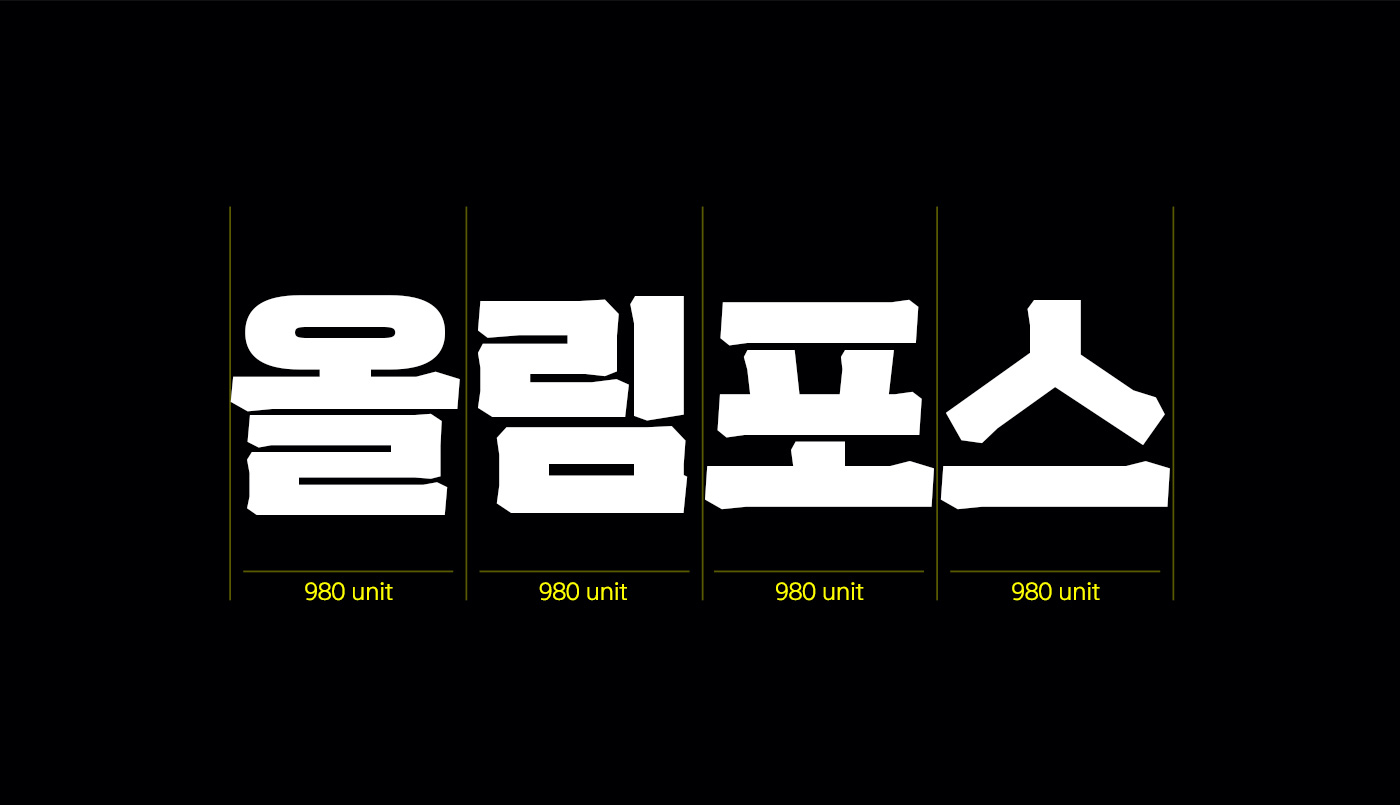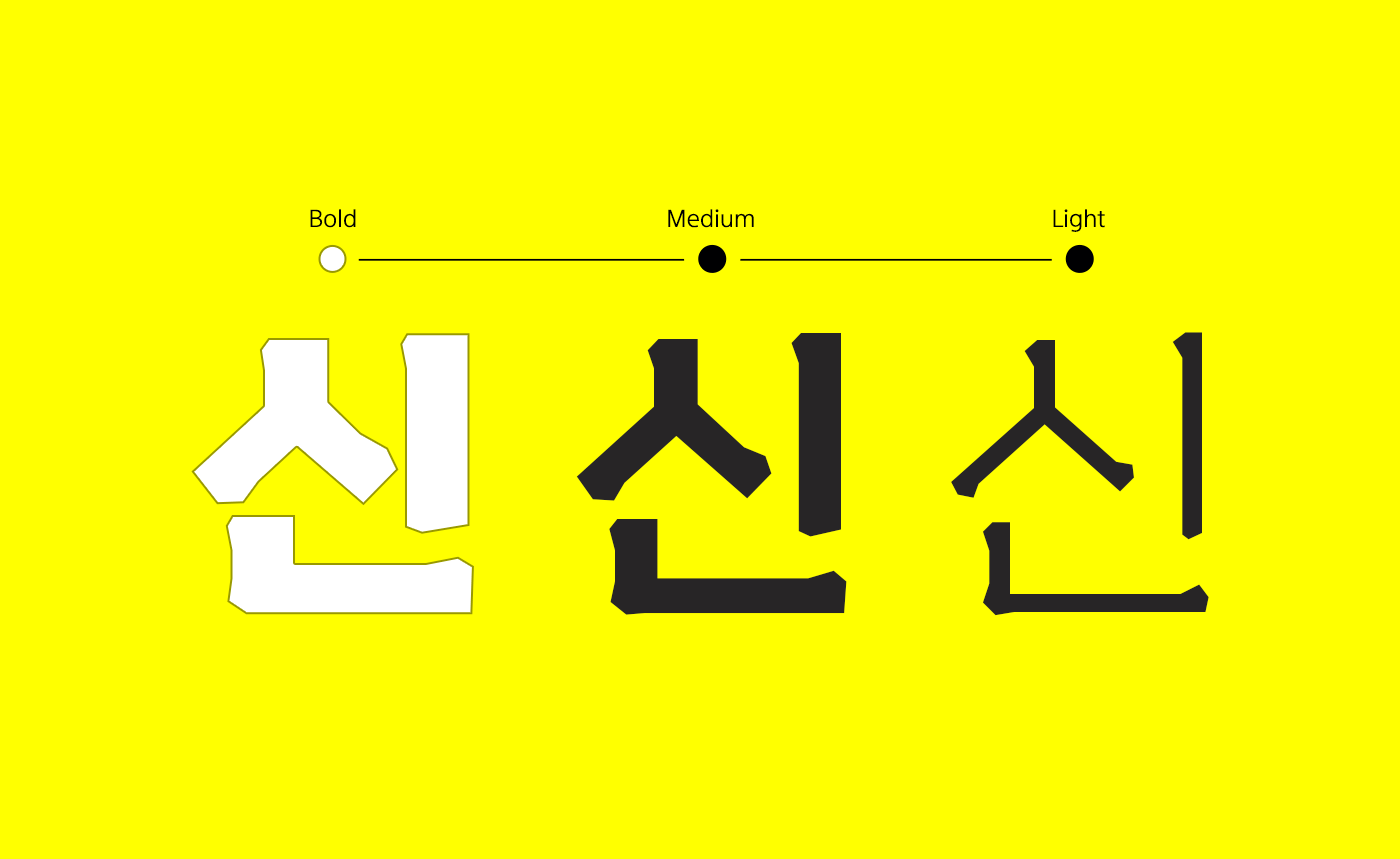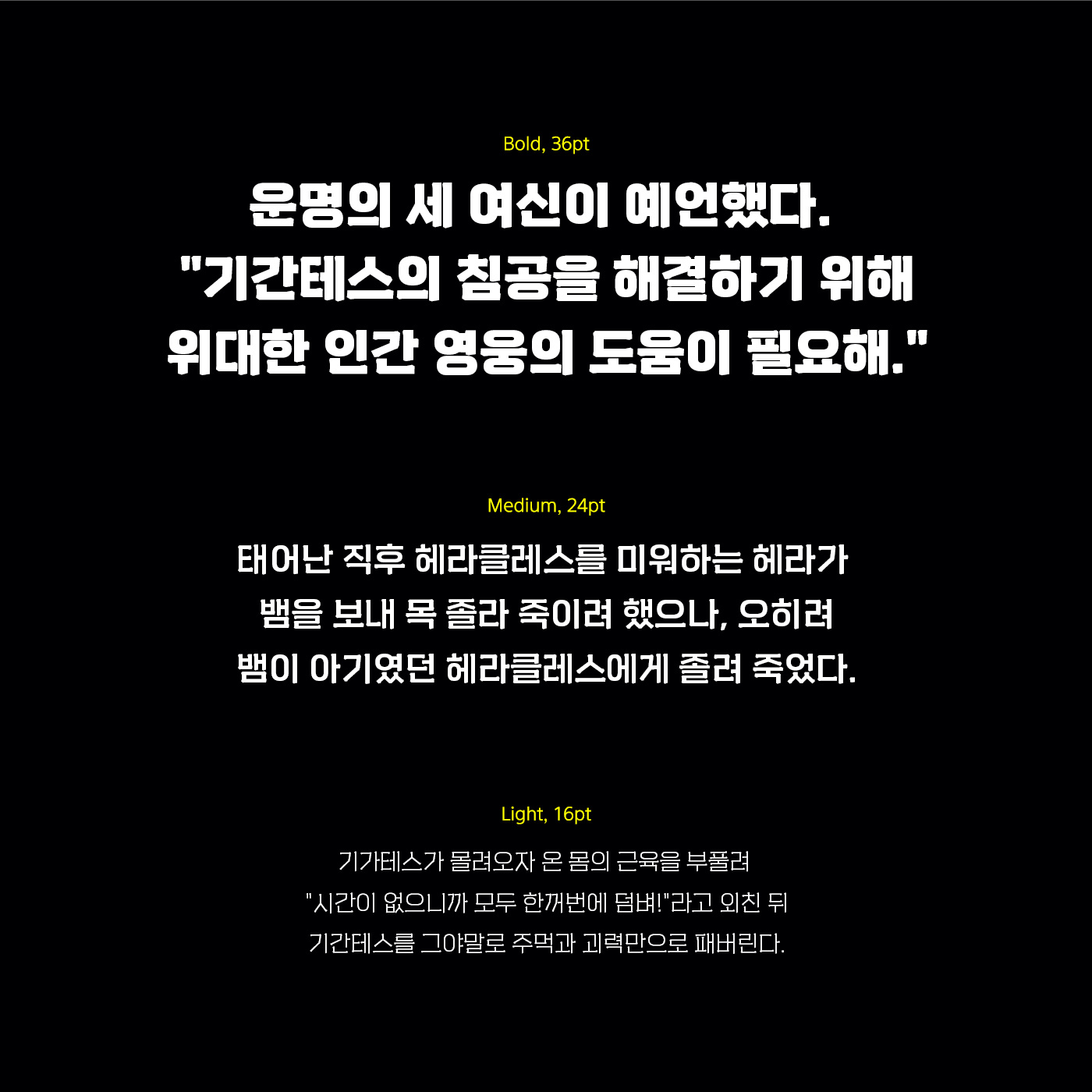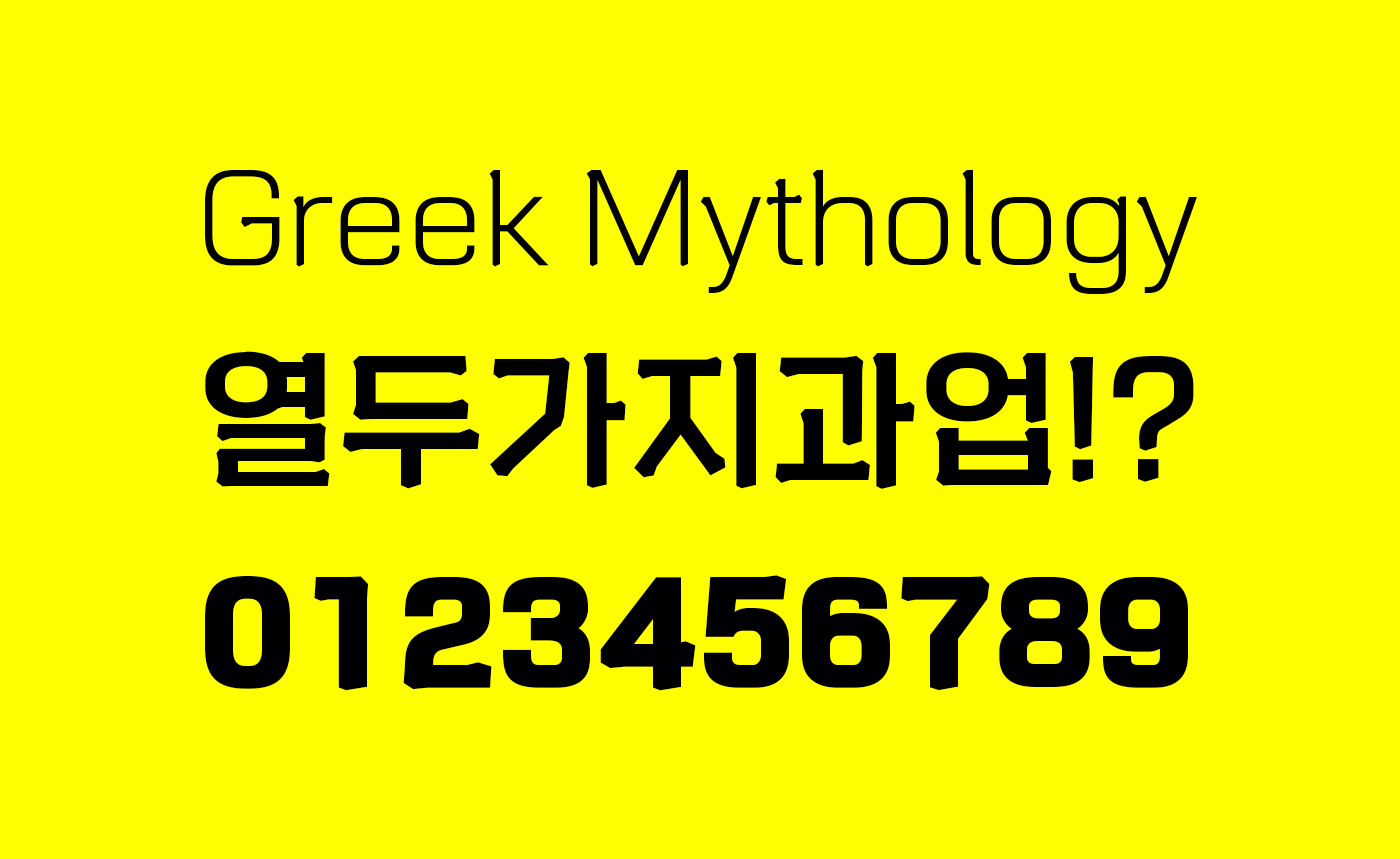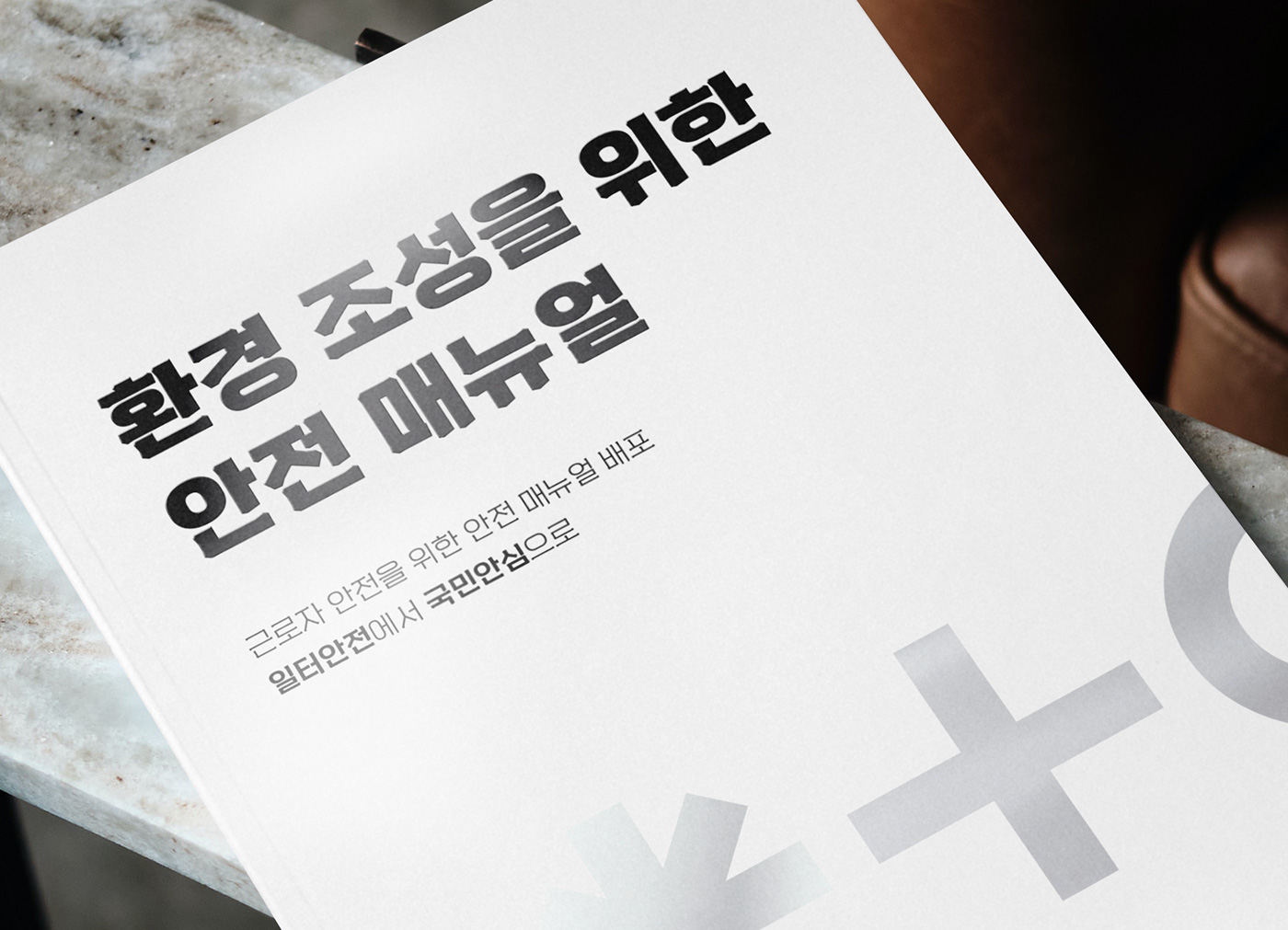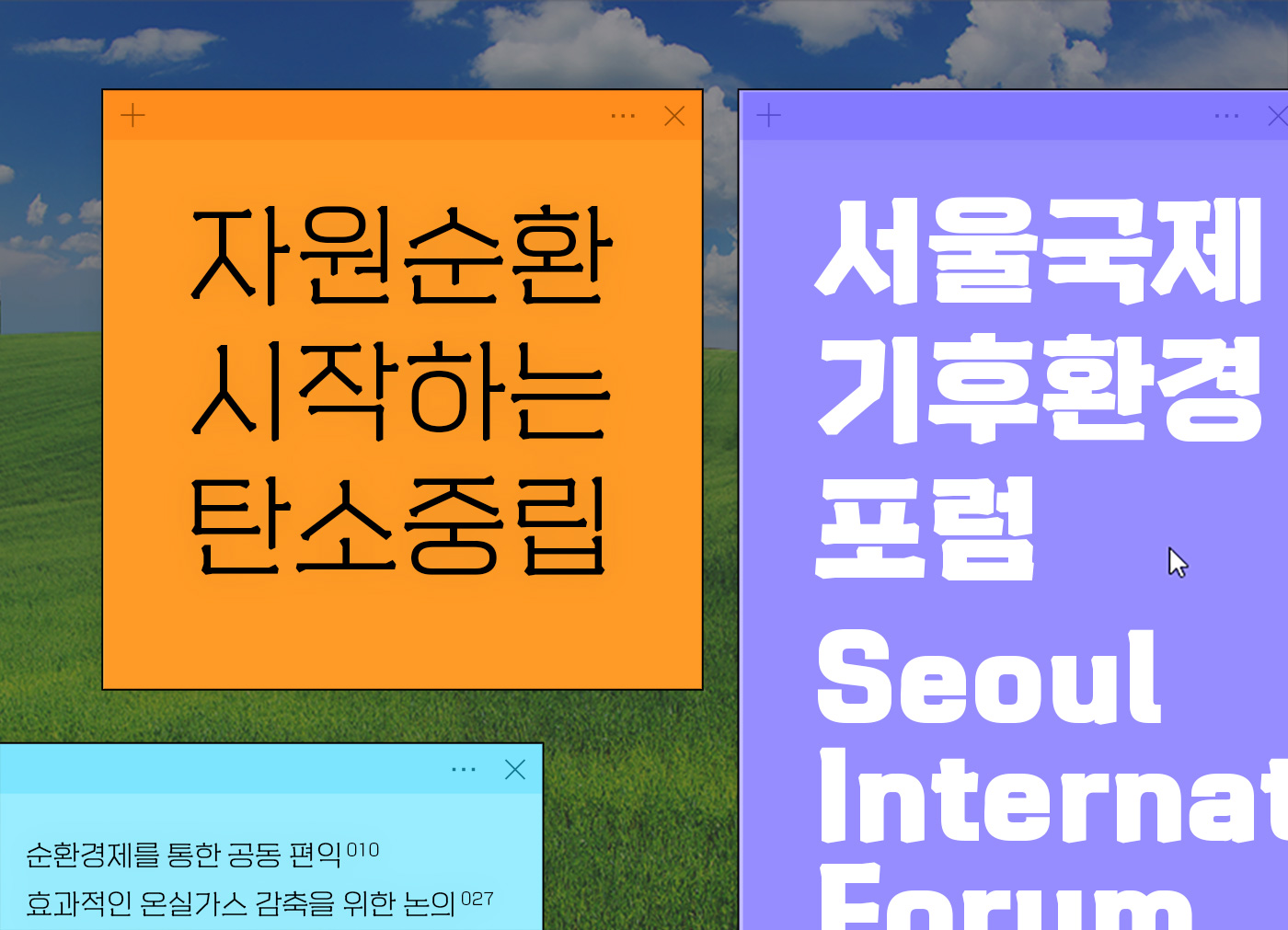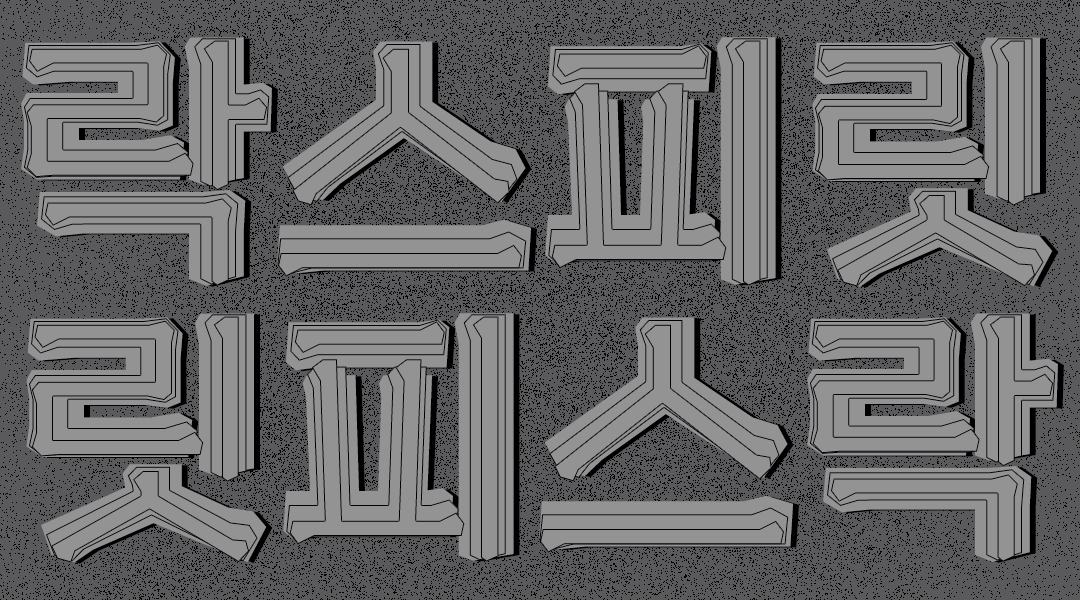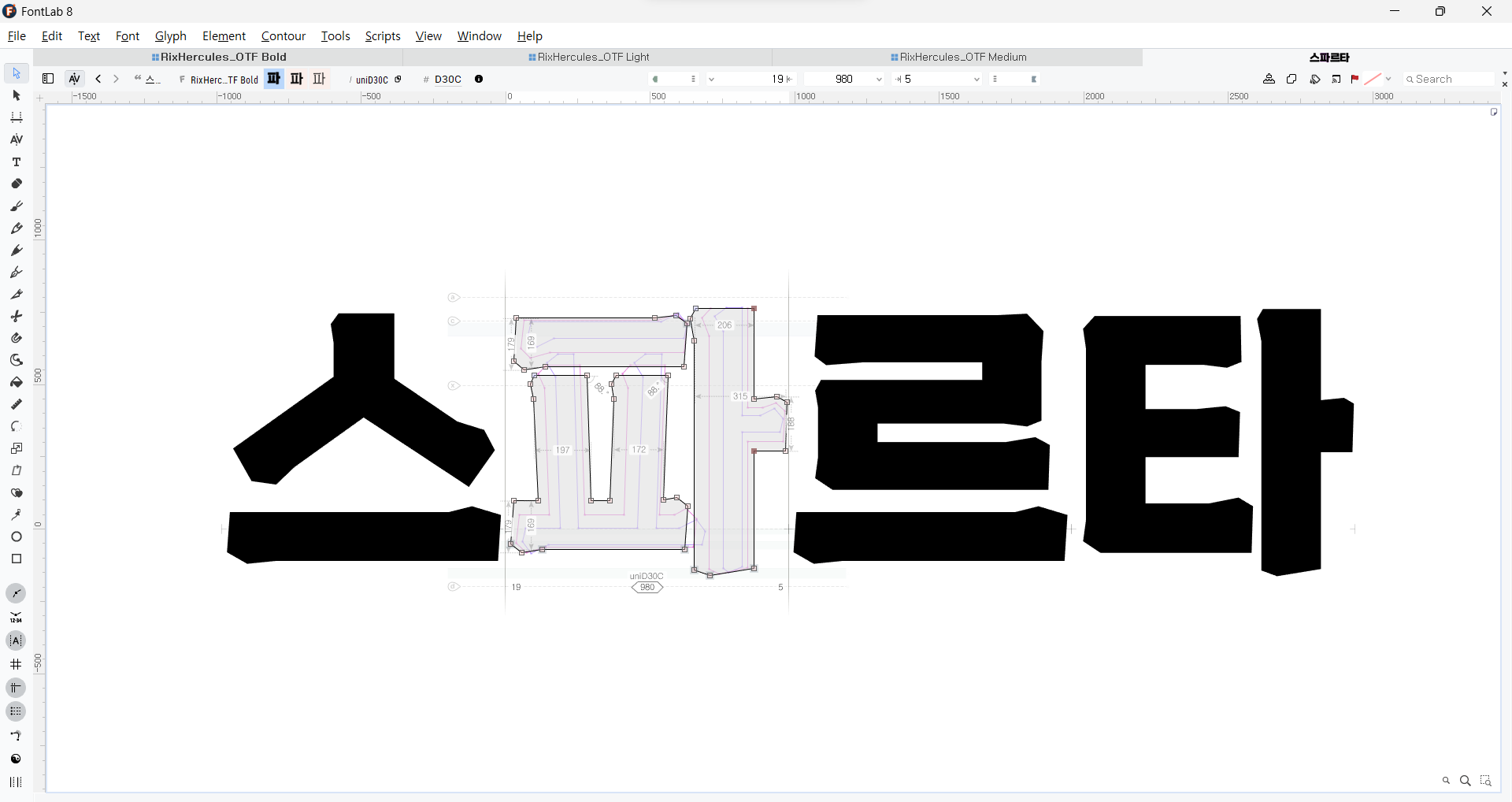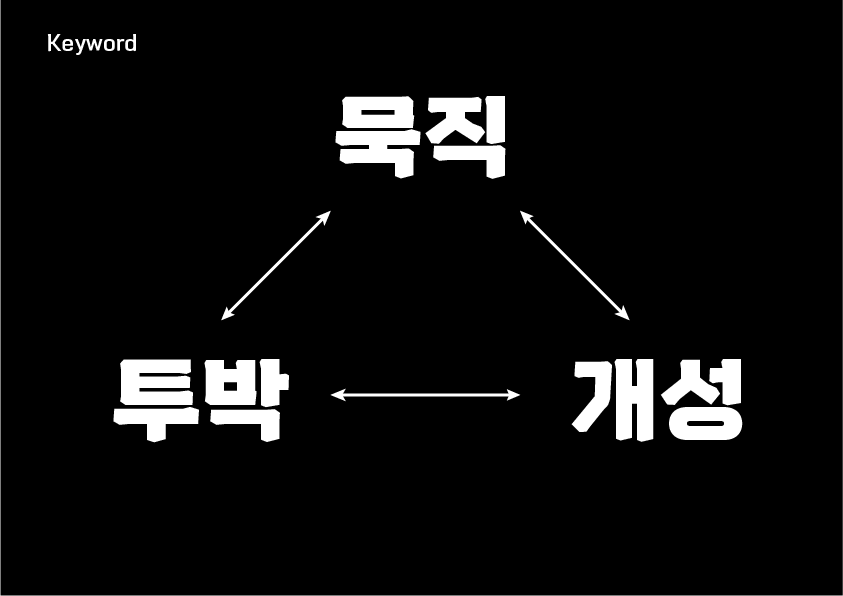
안녕하세요. 오늘은 여름의 끝자락을 잡고 있는 9월의 신규 폰트 「Rix헤라클레스」를 소개합니다. 단단한 힘이 느껴지는 두꺼운 획과 투박한 개성이 느껴지는 디자인이 눈에 띄는 서체입니다. 이번 서체는 총 3가지 웨이트로 제작되어 활용성도 더욱 높을 것으로 기대되는데요, Rix헤라클레스 폰트를 기획하고 제작한 최법호 디자이너를 인터뷰를 통해 만나보겠습니다 :)
안녕하세요. 소개 한번 부탁드립니다!
안녕하세요. Rix스크린-VF에 이어 Rix헤라클레스로 다시 돌아온 폰트디자이너 최법호입니다. 반갑습니다.
Rix헤라클레스는 어떻게 기획한 서체인가요?
평소 운동을 좋아하던 저는 ‘진짜 남자다움을 표현한 서체를 제작해 볼까?’라는 호기심을 시작으로 아주 강하고 묵직하고 투박한 서체를 만들고 싶어 기획하게 되었습니다. 그렇게 ‘묵직함, 투박함, 개성’을 세 가지 키워드로 설정하고 남자다움의 다양한 이미지를 참고하여 폰트에 적용해 보려 노력하였습니다.
폰트명은 왜 헤라클레스인가요?
그리스 로마 신화의 전설, 영웅의 대명사로 가장 유명한 인물이라고 할 수 있는 헤라클레스*는 힘과 영웅의 신으로 제 기획 의도와 가장 적합하다고 생각했습니다.
*헤라클레스(Hercules/Heracles)
그리스 신화의 영웅이자 신으로 여러 신화 속 영웅 가운데서도 실질적으로 영웅의 대명사로 군림하는, 지구 전체의 신화와 전설에서 가장 유명한 사나이라 할 수 있다. 신화상에서 보여준 용력과 능력이 대단하다보니 세상에서 가장 힘이 센 사람의 대명사격으로 사용하기도 한다.
3가지 굵기로 제작한 이유와 각각의 웨이트를 어떻게 잘 활용하면 좋을지?
처음에는 가장 두꺼운 굵기만 제작하다가 이 서체를 사용자가 더 다양하게 활용할 수 있게 라이트, 미디엄 순으로 굵기를 추가하여 총 3종으로 제작하였습니다. 두꺼운 획에서는 묵직함이 잘 표현된다면, 얇은 획은 강함을 유지하면서도 개성이 좀 더 드러나게끔 의도하였습니다. Rix헤라클레스는 어느 굵기든 힘 있고 주목도가 높은 폰트라 포스터 디자인, 영상 섬네일에 사용하면 좋을 것 같아요. 세 가지 굵기로 다양한 분야에 활용해 보세요!
이번 폰트를 제작하면서 느낀 점 또는 앞으로의 계획?
힘과 영웅의 신, 헤라클레스🪨
Rix헤라클레스는 큰 바위처럼 단단하고 각이 있는 글자 디자인과 두꺼운 획으로 높은 주목성을 갖고 있습니다. 980 unit의 비교적 넓은 폭으로 안정감이 있으며 투박한 듯 묵직한 바디감이 특징입니다.
세 가지 웨이트가 각각 다른 느낌을 주는데요, 디자이너의 제작 의도대로 Bold로 갈수록 더 단단하고 묵직한 힘이 느껴지고 Light로 갈수록 개성 있는 디자인이 도드라지는 것을 느낄 수 있습니다. 굵기에 다양성을 주어 제목용부터 본문용까지 여러 범위에 사용할 수 있습니다.
한글과 혼용 시 조화로운 디자인이 가능하도록 영문과 숫자, 일부 기호에도 동일한 특징을 적용했습니다.
이렇게 활용해 보세요⚡
주목성이 필요한 포스터 헤드라인과 본문에 동일한 폰트를 다른 웨이트로 사용하여 일관성 있는 디자인이 가능합니다. 강함과 개성을 동시에 갖고 있어 색다른 분위기를 줄 수 있습니다.
웹페이지, 배너, SNS 콘텐츠 등 메인 썸네일로 쓰기에 좋은 Bold, 서브 텍스트나 자막으로 쓰기 좋은 Medium, Light까지 정말 다양한 활용도가 기대되는 Rix헤라클레스 폰트를 만나보세요!